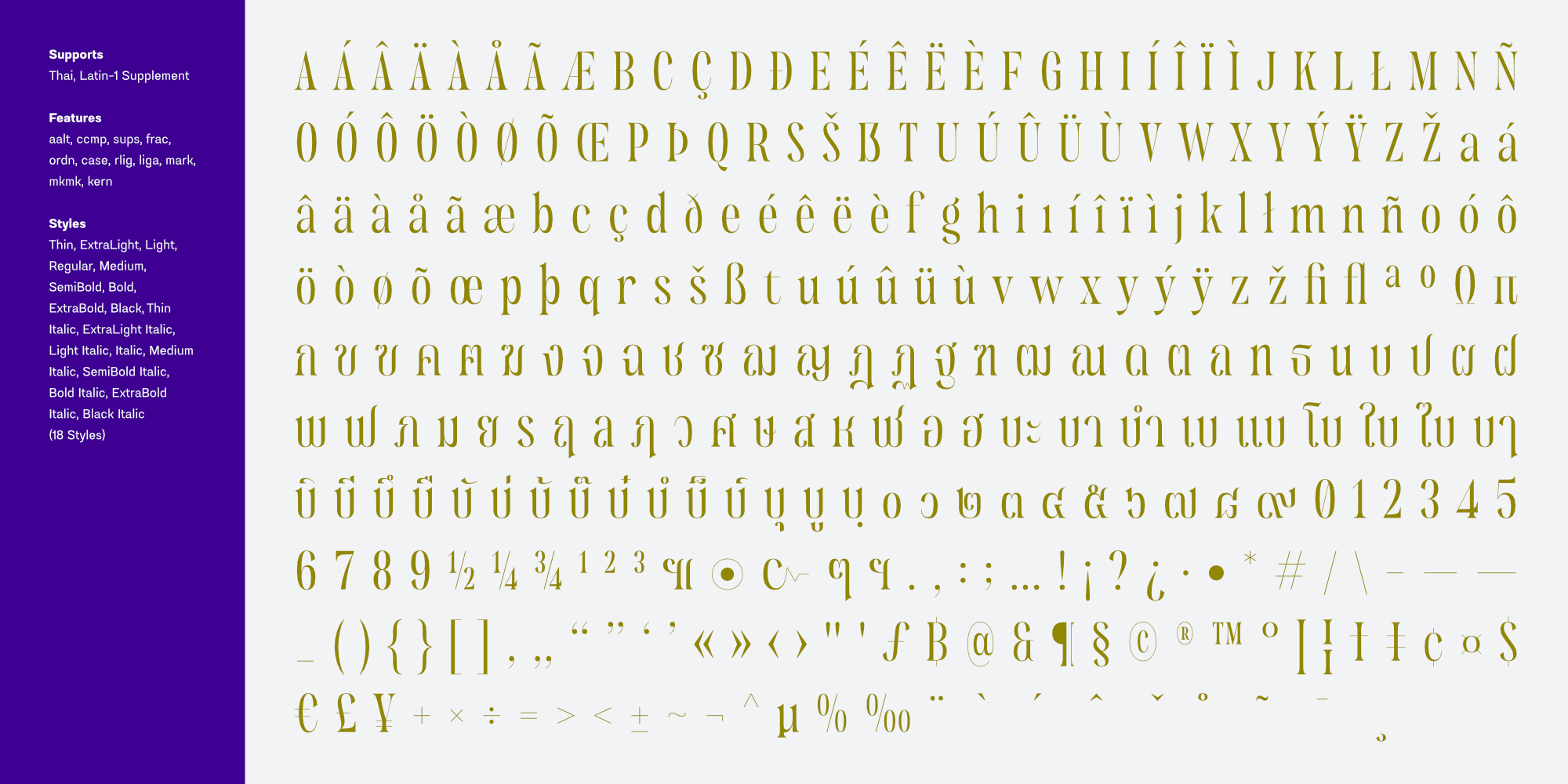
วิจิตรา | Wichittra
ชื่อฟอนต์ : วิจิตรา | Wichittra
วิจิตรา เป็นแบบอักษรเซอริฟแบบแคบคอนทราสสูง ชื่อของแบบอักษรนี้มาจากชื่อทั่วไปของผู้หญิงไทย ซื่งมีความหมายว่า 'สวย' หรือ 'งดงาม'